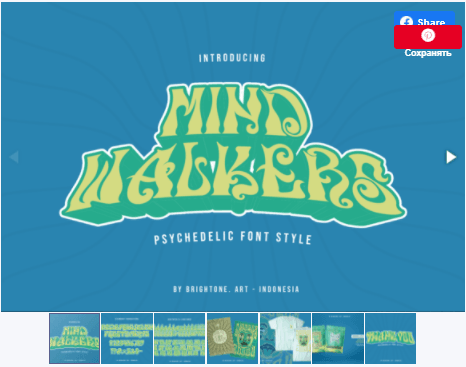
Mind Walkers Font
Mind Walkers — это психоделический дисплейный шрифт с потрясающим стилем. Используйте его для создания выдающихся логотипов, дизайнов рубашек, дизайнов сумок, этикеток, наклеек, брендинга и многого другого.